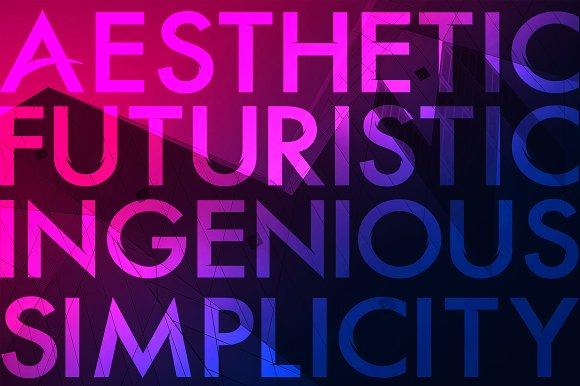
Creativemarket Astronova Font
[Creativemarket] Astronova Font
Astronova-это шрифт sanserif, который отличается минимализмом, простотой и современным стилем. Вдохновленный ультрасовременным и современным внешним видом с простой настройкой царапин на формах. Доступен в обычном и курсивном стиле.